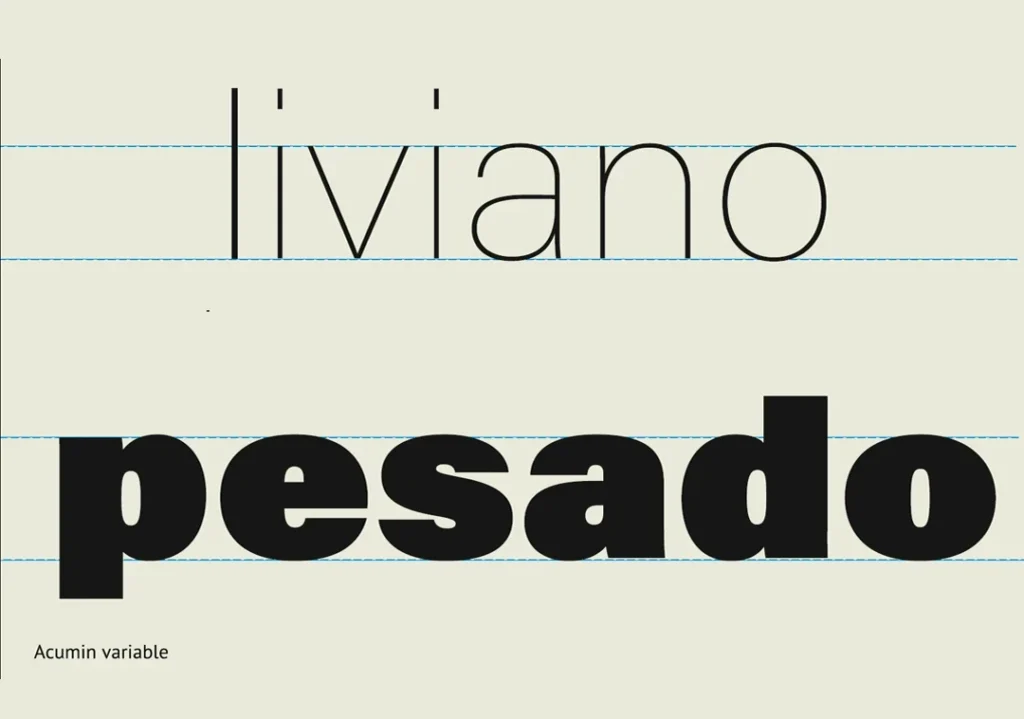
BOLD
Es una variable de peso. Es español es negrita aunque es muy habitual denominarla por su nombre en inglés. Morfológicamente se caracteriza por la preponderancia de los trazos gruesos.